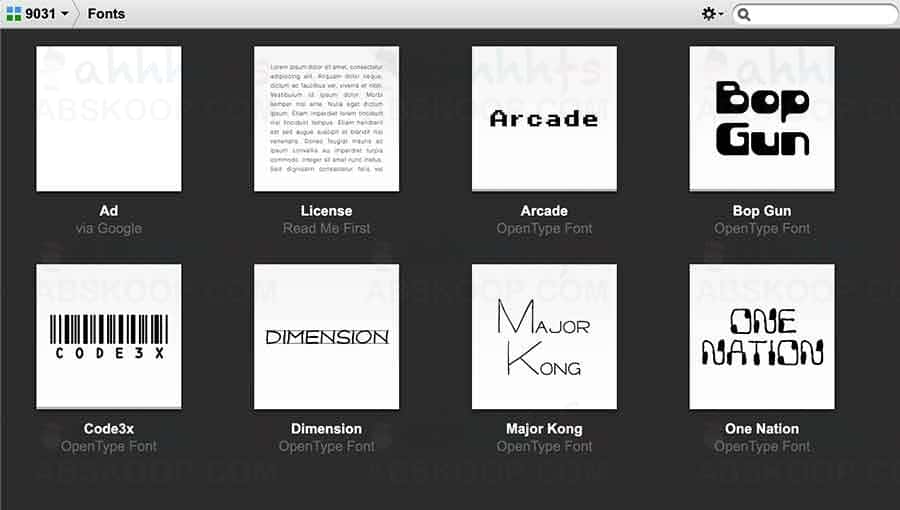
6款可商用特殊英文字体资源:打破常规视觉风格,支持免费下载应用
9031 Fonts 由日本设计师足立裕司创立,提供六款风格独特且完全免费的英文字体,支持个人及商业用途,是设计师寻找个性化视觉元素的优质资源库。
字体资源概览
该网站提供了六款核心字型:Arcade、Bop Gun、Code3x、Dimension、Major Kong 以及 One Nation。为了满足不同的设计需求,每款字体均涵盖了多种变体样式,包括:
• 一般样式 (Regular): 标准设计版本。
• 圆角 (Rounded): 边缘更柔和,视觉感更亲和。
• 倾斜 (Oblique): 增加动态感与速度感。
• 点阵 (Dot Impact): 模拟复古电子屏幕或打印效果。